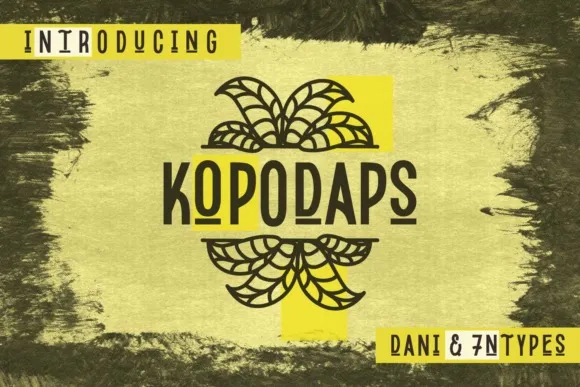
A Kopodaps Font é uma elegante fonte séria que combina elementos modernos com um toque nostálgico. Ela foi criada por Dani (7NTypes) e disponível para download na plataforma de crowdsourcing 99designs, perfeita tanto para designers quanto para estabelecimentos comerciais. Suas linhas retas e clean fazem dela uma escolha ótima para ambientes modernos e retro, como capas de livros, adesivos ou materiais de embalagem. Também é ideal para criações que exigem um equilíbrio entre modernidade e rusticidade, como posters, camisas personalizadas e símbolos de citação. Suas linhas simples são ideais para qualquer design que precisa de uma composição moderna e minimalista, tornando-a perfeita não apenas para a web ou em impressões digitais, mas também para aplicação em materiais físicos como papel ou tecido. Composta com precisão e cuidado, Kopodaps é um recurso gráfico versátil que enriquece qualquer projeto de design sem deixar de lado sua elegância estilizada.